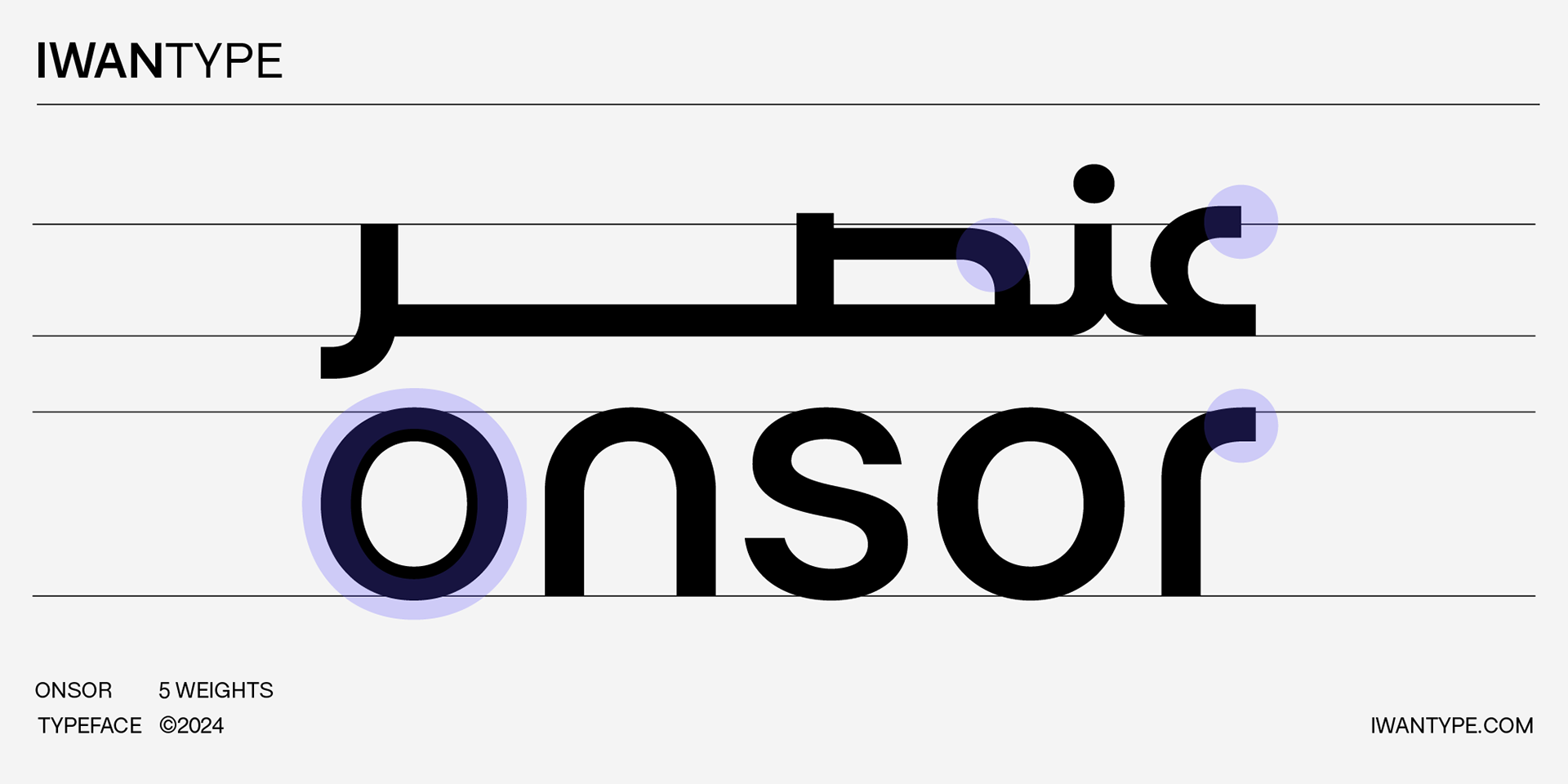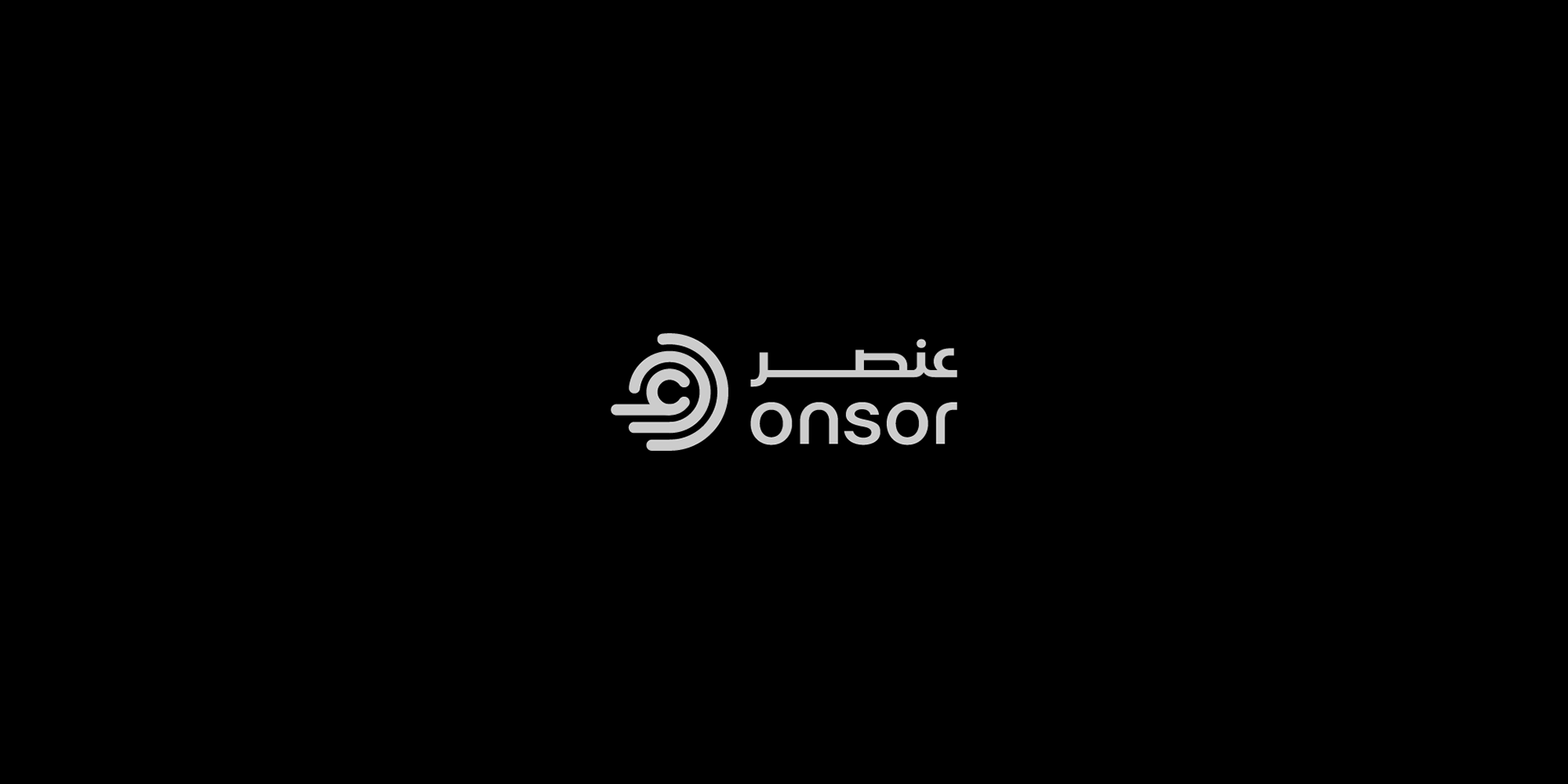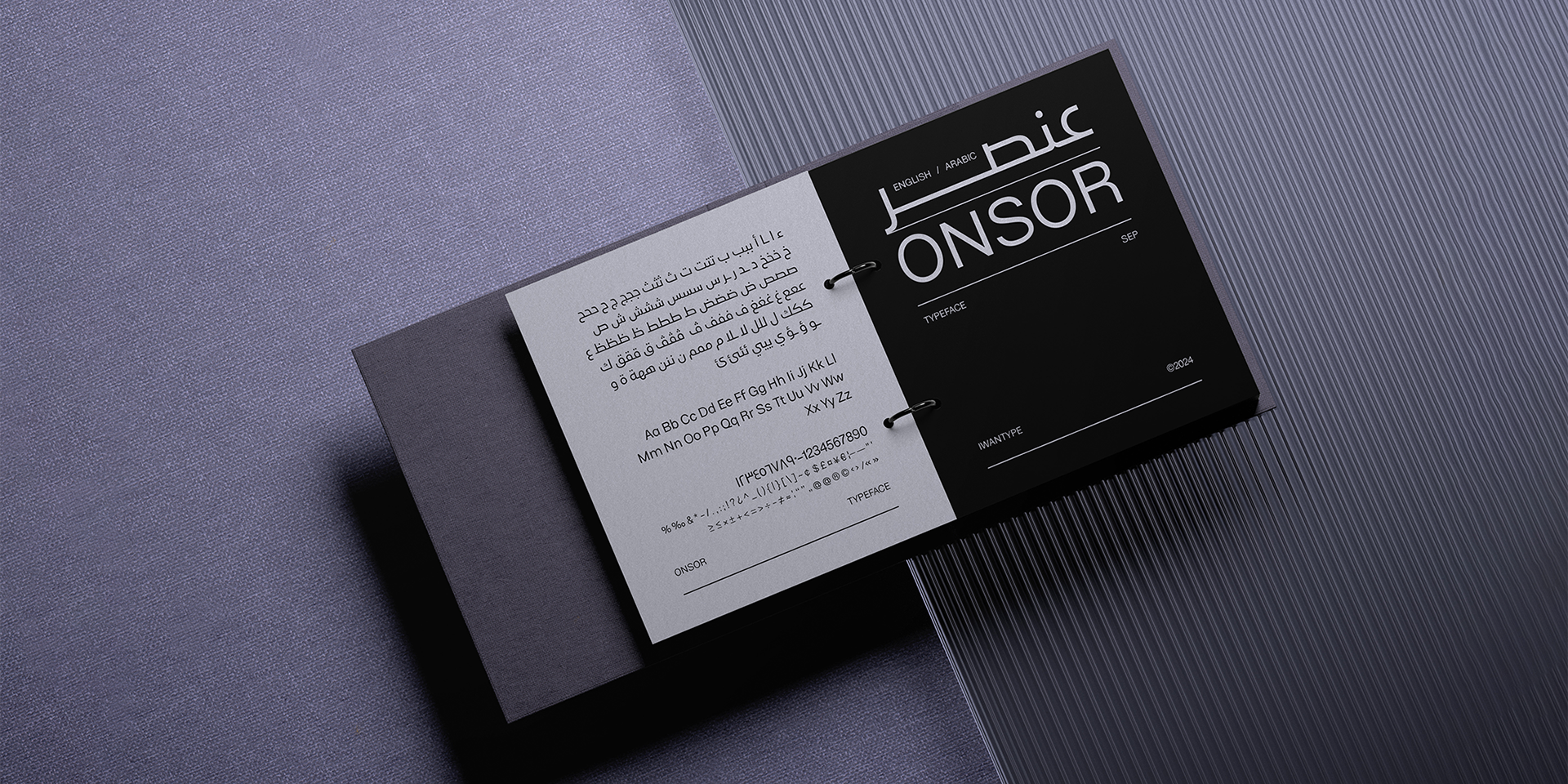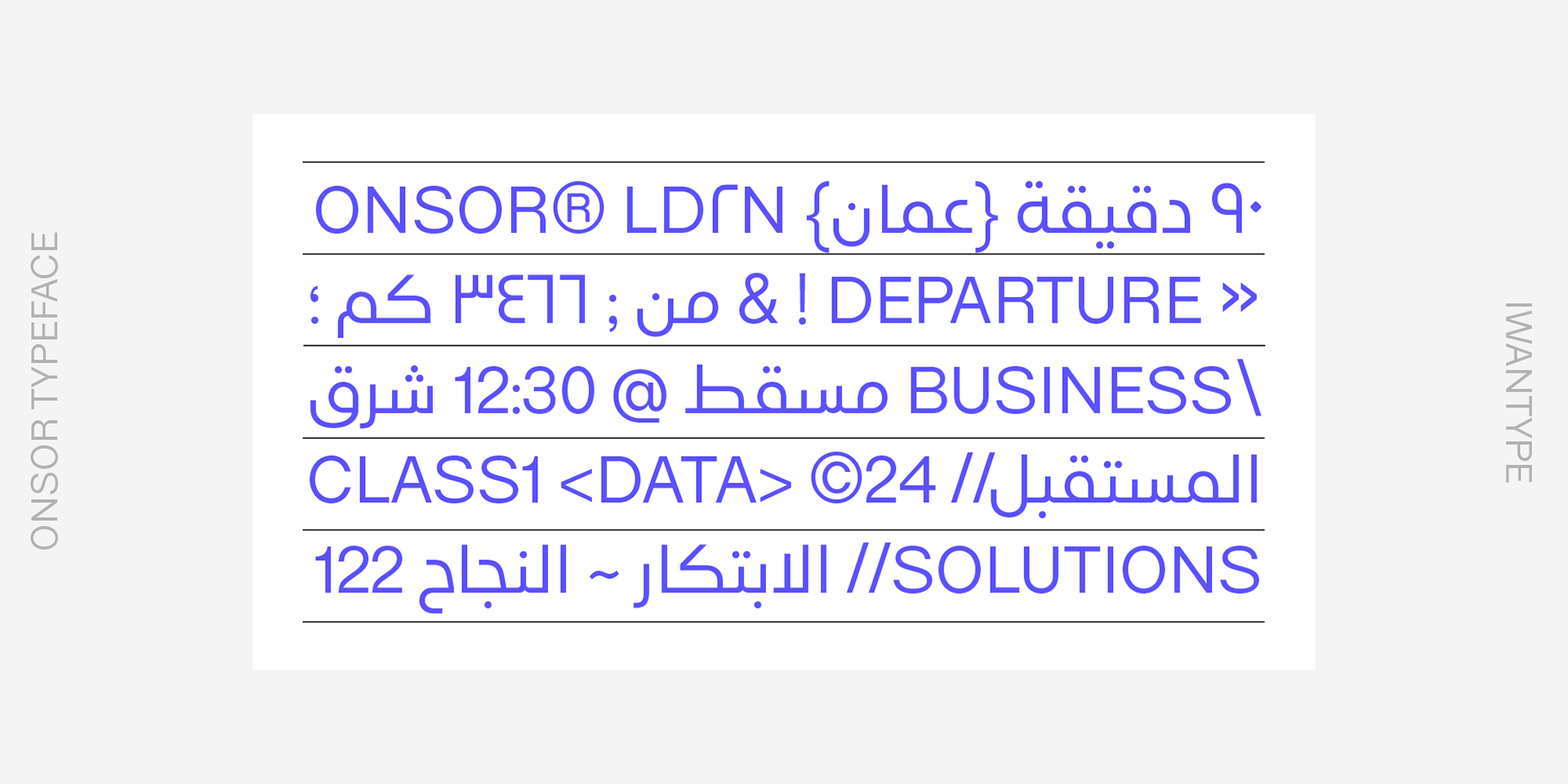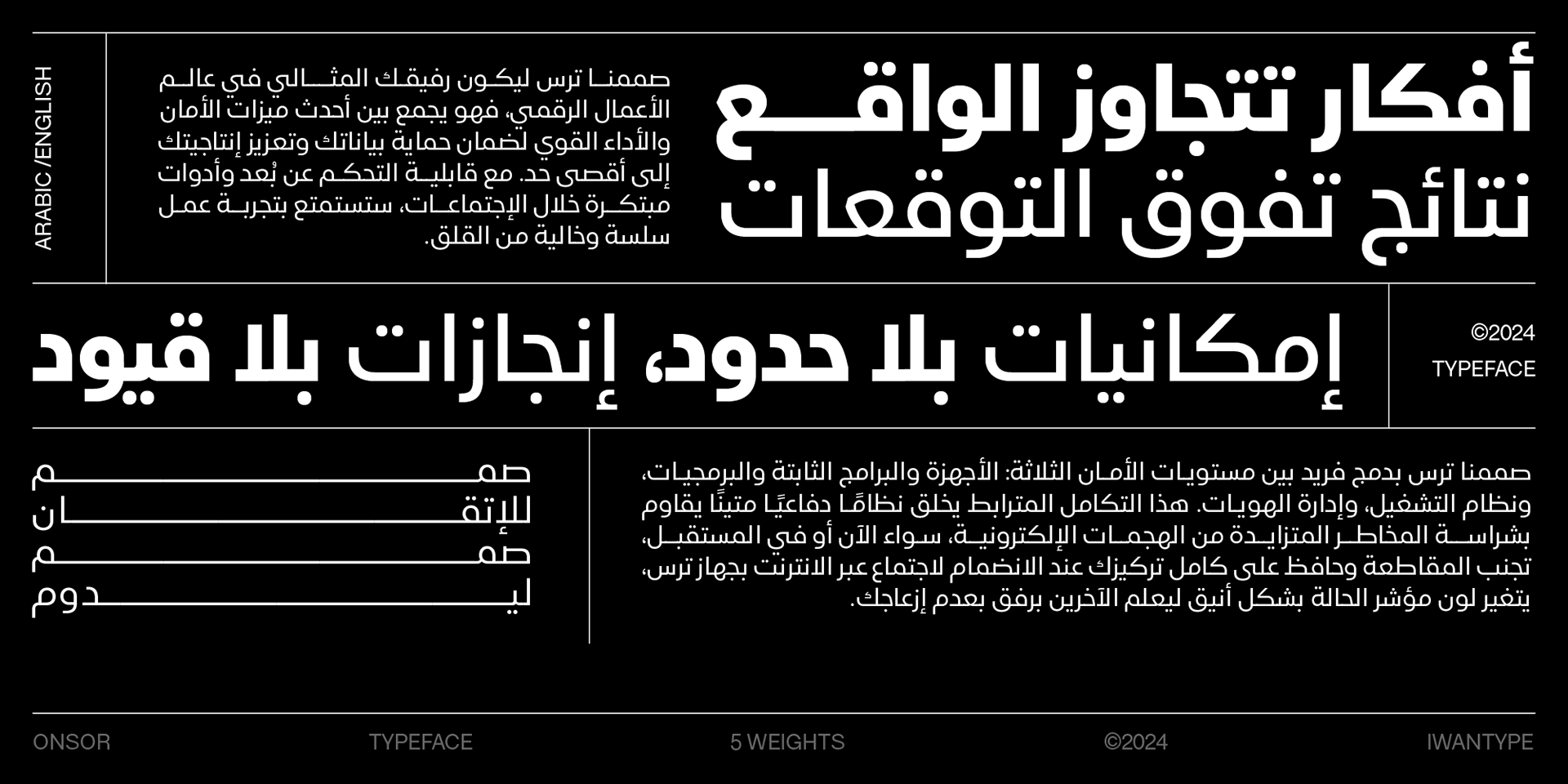
تحديث شعار شركة عنصروتصميم خط طباعي خاص
تحديث شعار شركة عنصر ليصبح أكثر بساطة وفعالية. تم الحفاظ على الفكرة الأساسية للشعار مع تطوير تصميمه ليلائم الاستخدامات المختلفة. كما تم تصميم خط طباعي جديد يعكس هوية الشركة.
وصممنا في إيوان تايب خطًا طباعيًا مخصصًا لشركة عنصر، يجمع بين جماليات الخط العربي وبساطة الخط اللاتيني. يهدف هذا الخط إلى تعزيز هوية الشركة وعكس روحها الهندسية. يتكون الخط من خمسة أوزان مختلفة لتلبية متطلبات التصميم المتنوعة، مما يمنحه مرونة عالية في الاستخدام.